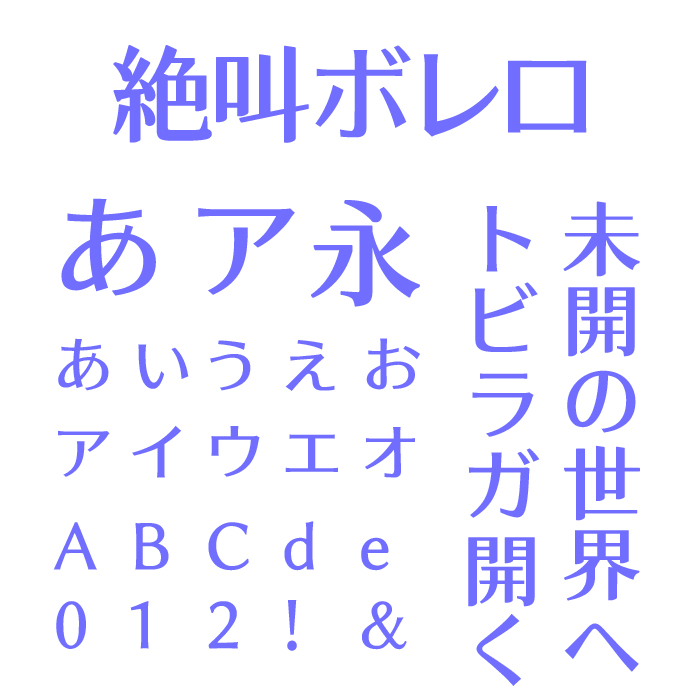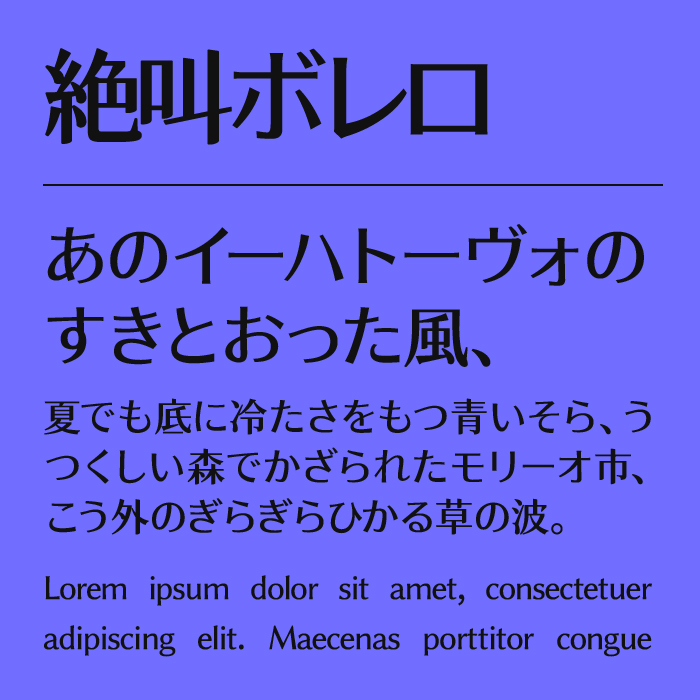
絶叫ボレロフォントは、漢字「獅尾四季春加糖JP」フォントとひらがな・カタカナ「源暎ラテゴ」フォントを組み合わせて作られた合体フォントです。
フォーク体のようなどこかクラシカルで気品を感じさせる佇まいを感じさせるフォントです。マンガのセリフ向けとして開発されたので、吹き出しフォントとして最適なフォントです。
フォントの文字見本
収録文字は、漢字・ひらがな・カタカナ・アルファベット・数字・記号が収録。